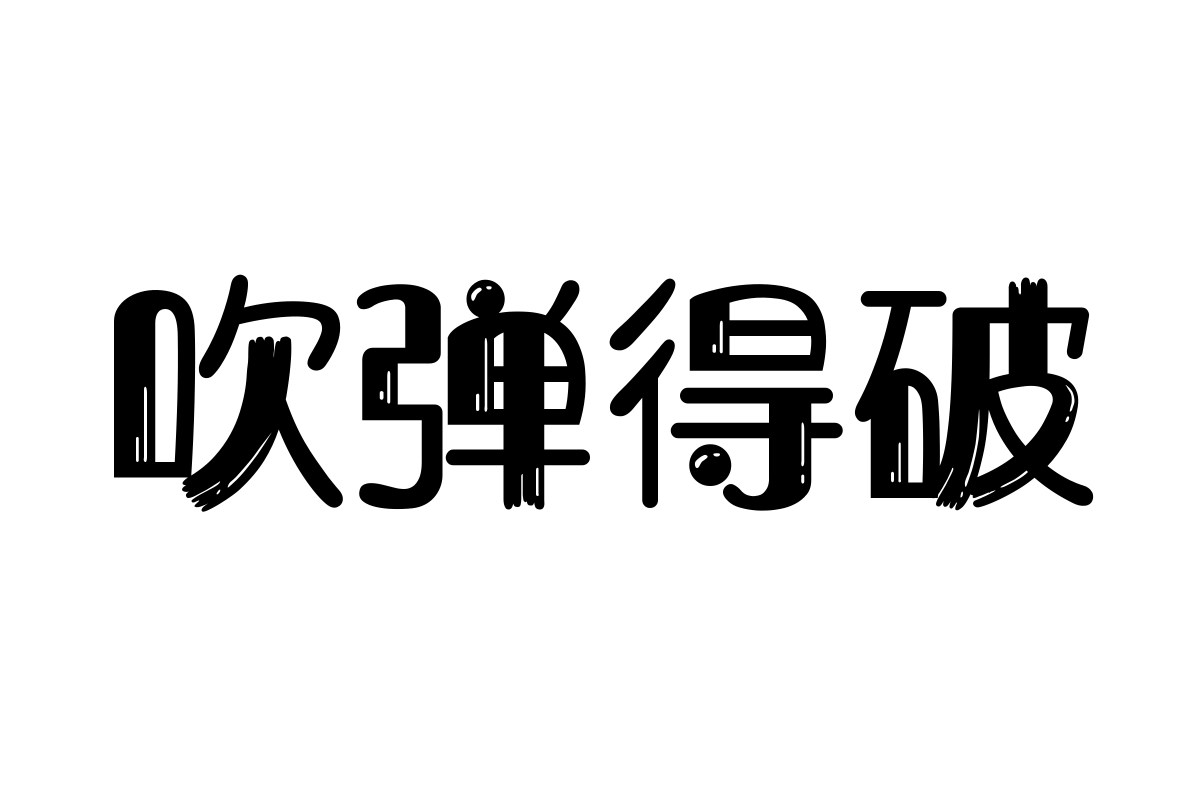
汉仪星球体字体是一款具有独特风格的中文字体。这款字体采用了现代的设计元素,使得文字看起来更加时尚和动感。它的笔画流畅,字形饱满,给人一种强烈的视觉冲击力。
汉仪星球体字体适用于各种需要强调个性和创意的场合,如广告、海报、网页设计等。它的独特风格能够吸引人们的注意力,使作品更具吸引力。
此外,汉仪星球体字体还具有很高的可读性。它的笔画粗细适中,间距均匀,易于阅读和理解。这使得它在各种应用场景下都能够发挥出良好的效果。
总之,汉仪星球体字体是一款非常实用的中文字体,无论是在设计还是商业领域都有着广泛的应用前景。